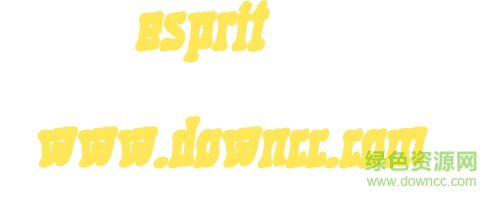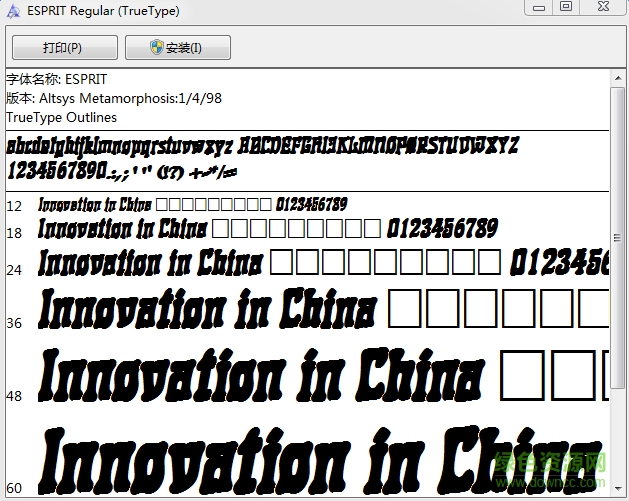
esprit字體是一種比較實(shí)用的電腦英文字體,寫(xiě)出來(lái)的字是如此的俊秀,而且很耐看,用于書(shū)法寫(xiě)作很不錯(cuò)哦,如果你喜歡書(shū)法,那么一定要經(jīng)常使用該字體,他能讓你的字體變得充滿韌性。歡迎喜歡的朋友來(lái)綠色資源網(wǎng)下載。